Römische Schrift
Mit den Legionen Roms verbreitete sich das lateinische Alphabet über fast den gesamten Kontinent. Bis heute prägt es die Schrift unzähliger Sprachen — von den 23 Buchstaben der Antike bis zu den 26 unseres modernen Alphabets.
Im Schatten des Imperiums
Das lateinische Alphabet
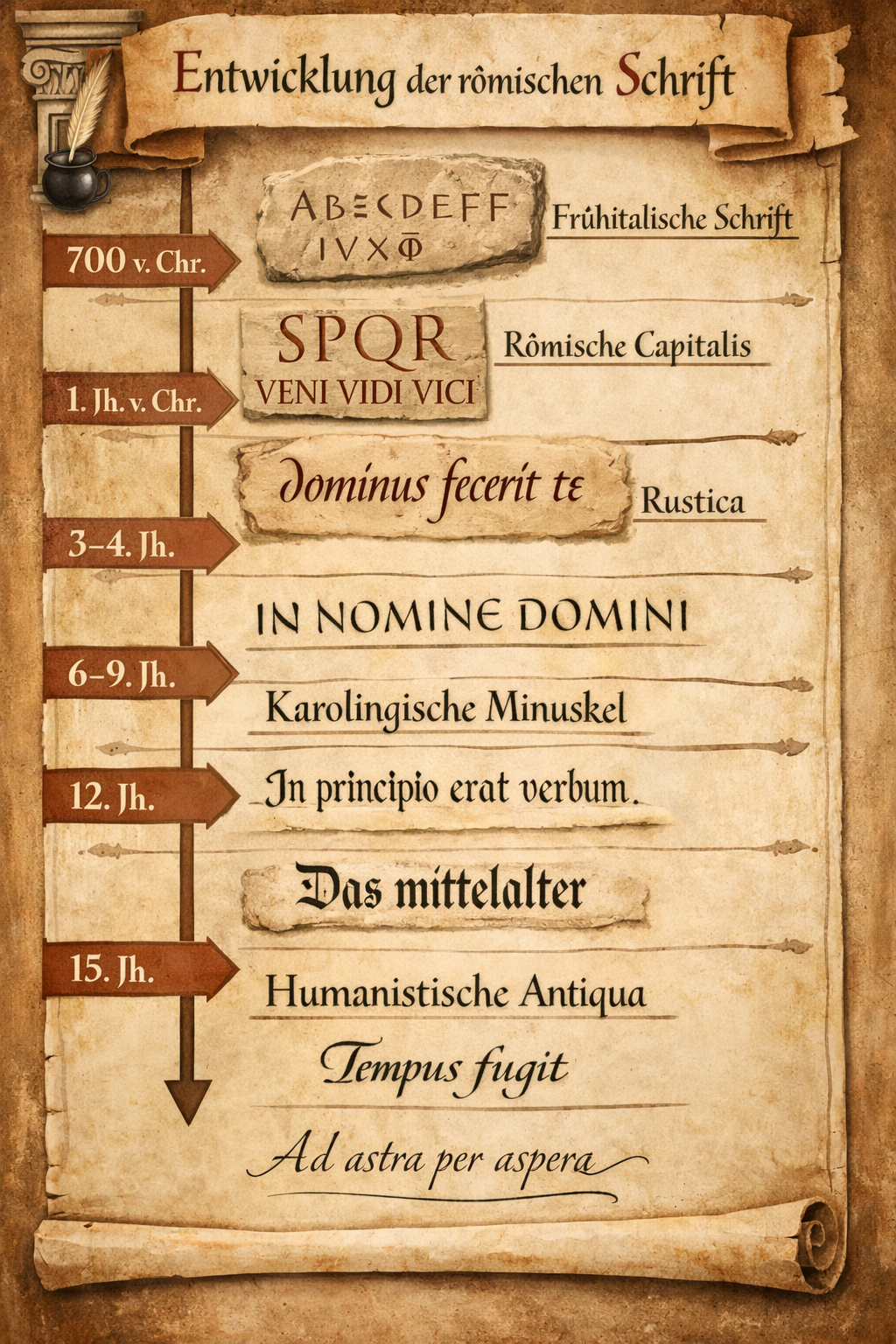
Antike & Mittelalter
Capitalis monumentalis
Aus dem etruskischen und griechischen Alphabet hervorgegangen, wurde die römische Schrift auf Triumphbögen und Grabsteinen meisterhaft in Stein gehauen. Aus ihr entwickelten sich Unziale, Karolingische Minuskel und schließlich die Druckschriften, die wir heute lesen.